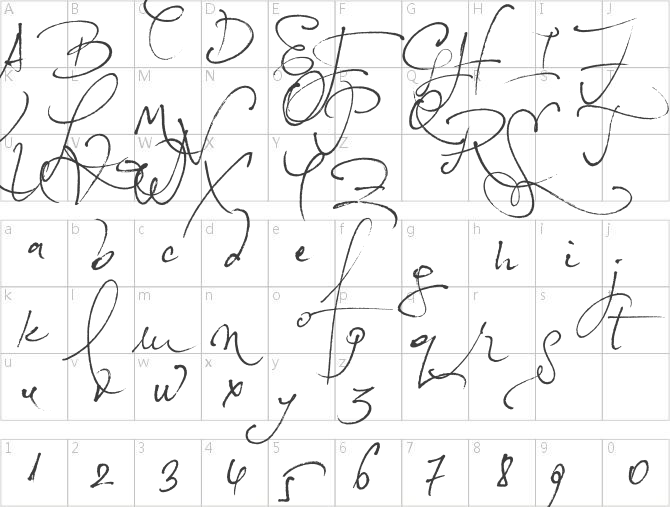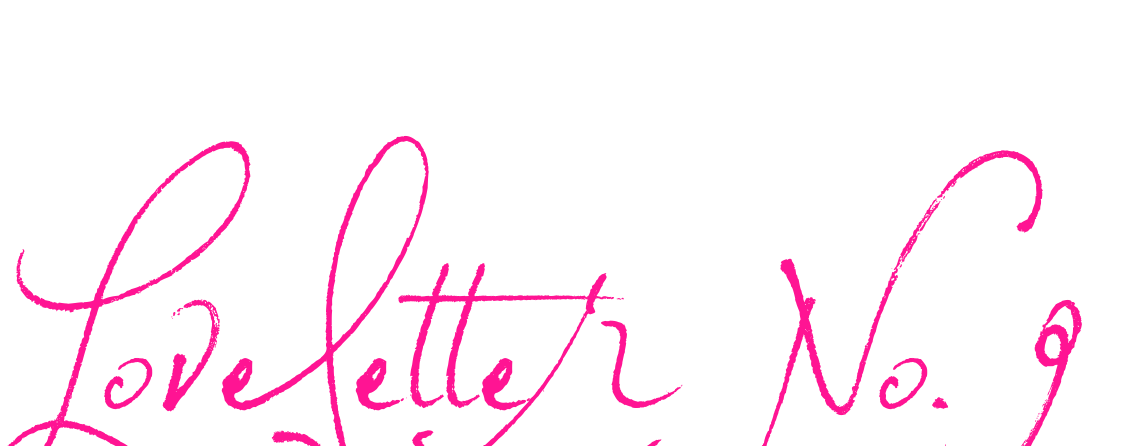
Loveletter No. 9 詳情頁
Loveletter No. 9
Loveletter No. 9介紹
Loveletter No. 9字體字庫是一款讓人賞心悅目、百看不厭的英文字體,適合各類廣告和產品包裝設計應用,字體大小0.35MB,格式為ttf字體,上傳用戶是曉語無聲,作者/版權方為未知